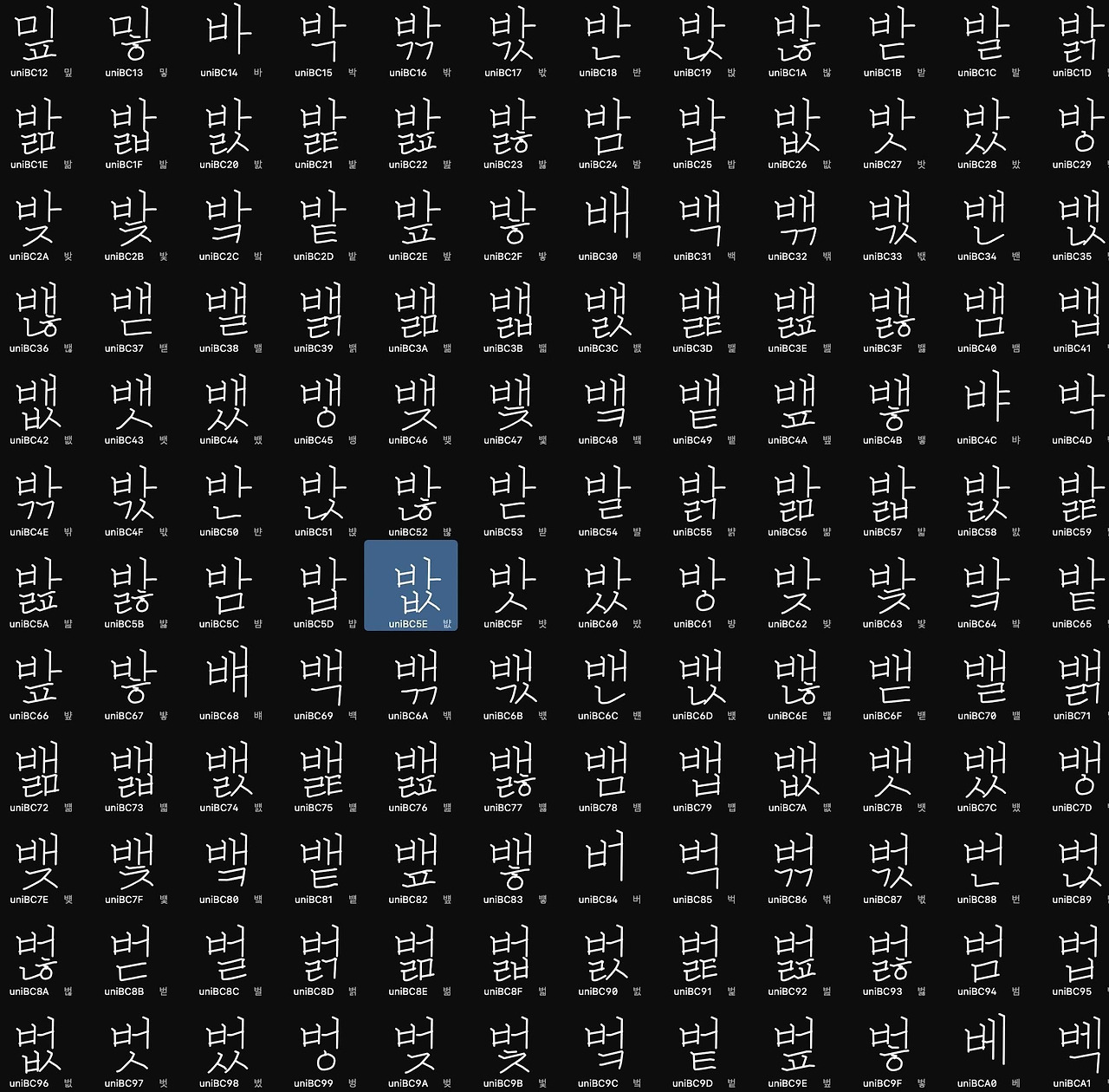
따라쓰기 폰트 필기체 제작
따라쓰기 폰트 결과물인 필기체 를 제작하고 다시
군대에서 수양록이라는게 있습니다. 그때 쓰던 글씨를 바탕으로 필기체를 만들었습니다. 세로쓰기를 주로 했었는데 그 기준으로 제작했습니다.
오늘 가이드가 되는 폰트가 완성되면 다시 따라쓰기 할 수 있는 점선으로 이뤄지고 원형 포인트가 있는 것과 점선으로 된 2종이 함께 마무리할 수 있으리라 봅니다.
손글씨는 바른 글씨교정용 폰트를 제작하는게 맞는거 같아서 난이도가 높아지고 가격이 말이 안될 수도 있겠다는 생각을 합니다. 제대로 교정하기 시작하면 몇일이 걸립니다.
교육+ 제작을 해주는게 맞을지 그냥 기념품이 되는게 맞을지 여러가지 생각이 오갑니다. 그냥 저는 기능형폰트를 만드는게 낫겠다 싶습니다.
그래서 주말에 폰트에 대한 최초의 생각을 발전시켜봤습니다.
손글씨가 아닌 스트로크 기반 폰트 방법론을 만들어 보고 있습니다. fill 이 아니고 stroke로 채우는걸 오직 기계가 이해할 수 있는 방식으로 설계중입니다.
머신이 이해하는 움직임이 이제 붙을 예정 CNC 콘트롤 데이터가 함께 들어가면 자수, 플로터, 레이저 등등 저 안에 간격을 채우는 기능은 최소한의 움직임과 기계인게 티가 안나게 몇개의 알고리즘을 사용
얇은 서체는 이제 손글씨용으로 만든 것도 방향을 잡았기 때문에 서체가 아닌 형태로 만들 수 있고 이번에는 영상용으로 내부적으로는 그림을 그리는 순서가 들어가게 됩니다. lottie 파일로 글자하나하나 순서대로 출력이 가능한 어플리케이션을 제작할 수 있으며 이 것을 figma, canva 등에 유료로 제공할 계획이 있습니다.
10년 전에 플래시로 획수 같은거 자동으로 만드는 것도 한 적이 있어서 글자 모든 것이 획으로 키네틱 애니메이션 스타일로 출력되게 할 수 있어 타사와 다른 경쟁력을 갖출 수 있을 것입니다.
외국인에게 한글을 재미있게 교육하겠다는 목표를 세웠기 때문에 대만인이 만든 Chineasy 처럼 hangul easy 라는 것을 만들 생각입니다.
한국사람에게 한국어는 쉽지만 사실 어려운 난이도의 언어라서 다른 개념을 가져와서 만들겁니다.